市谷の杜 本と活字館 企画展「秀英体111―秀英体ってどんな形?―」のお知らせ
「秀英体111―秀英体ってどんな形?―」
大日本印刷株式会社は、昨年2020年11月に印刷と本づくりを体感できる文化施設「市谷の杜
本と活字館」をオープンしました。「市谷の杜
本と活字館」は、DNPの事業の原点である活版印刷の職場を一部再現し、秀英体のデザイン、活字の鋳造から、印刷・製本までのプロセスを展示や、参加型ワークショップやイベントなど、来館者の皆さまに活版印刷を体感いただける機会を提供しています。
11月11日より、「市谷の杜
本と活字館」では、「秀英体111―秀英体ってどんな形?―」と題して、文字の形、秀英体の形に注目した企画展が開催されます。
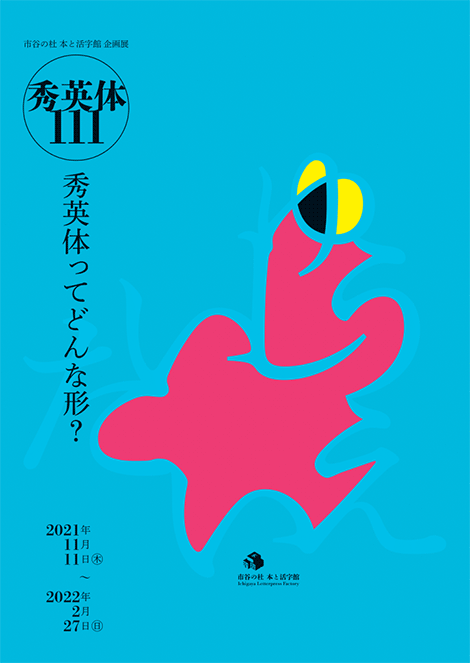
「秀英体111―秀英体ってどんな形?―」
文字について、文字の形について、考えてみたことはありますか?
ほとんどの人がおそらく無意識に眺めている文字にもいろいろな顔があります。それが書体です。大日本印刷は前身である秀英舎の時代から100年以上にわたって、オリジナル書体「秀英体」の開発を続けています。もともと活字書体として生まれた秀英体、活字の大きさや時代のニーズに合わせた豊富なバリエーションが特徴で、全活字書体が完成してから来年で111年を数えます。
秀英体と数多あるほかの書体とは何が違うのでしょう。秀英体の魅力とは何なのでしょう。本展では数あるバリエーションの中から、秀英体を代表する本文用の「秀英明朝」と見出し用の「初号明朝」の形に注目します。
「秀英明朝は一筆書きの“い”が特徴です。」などご紹介することもありますが、この展示会では、楽しみながら1文字1文字の形を見つめることができる展示が企画されています。また、会期中には、より深い内容のオンラインイベントも予定されております。